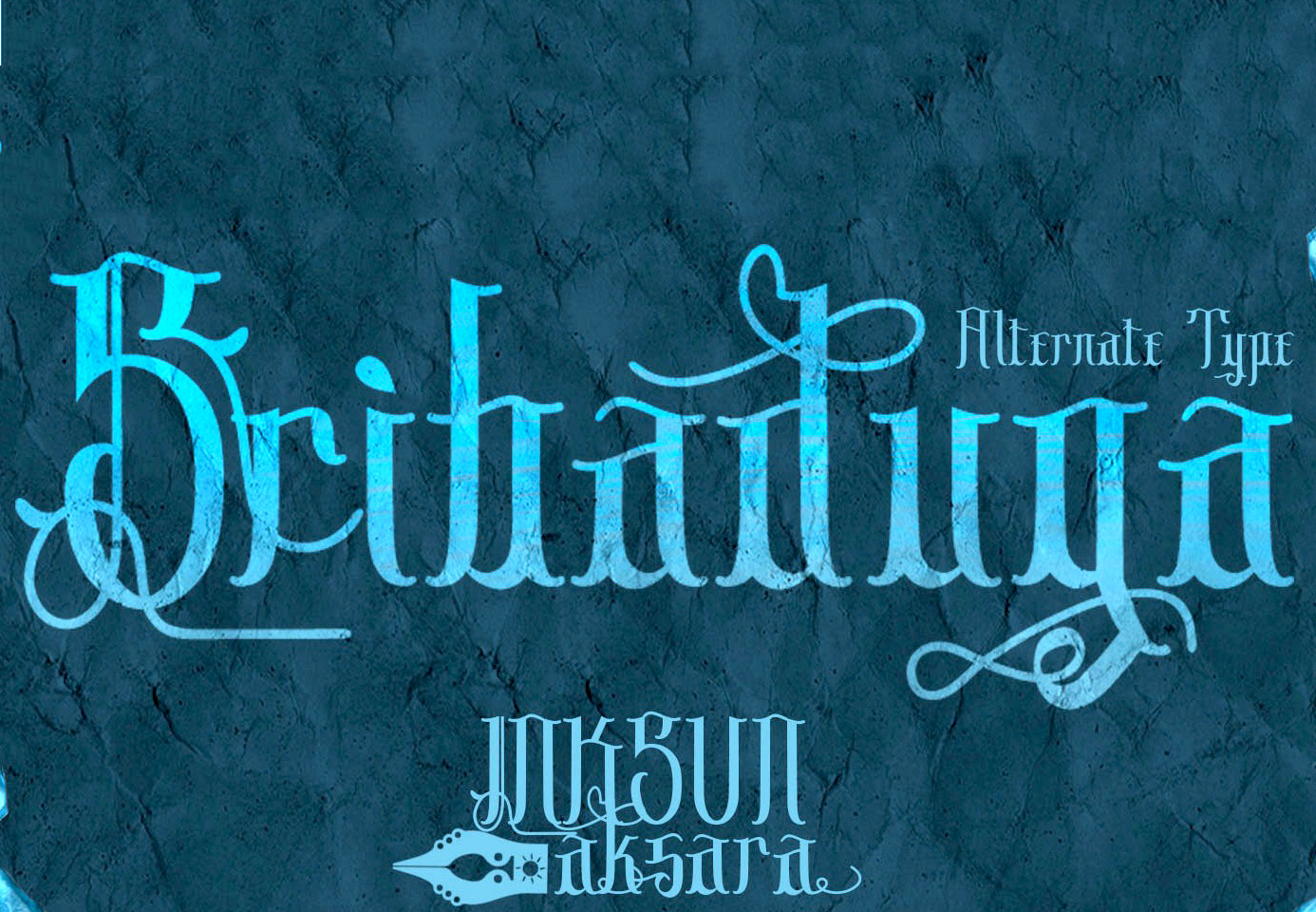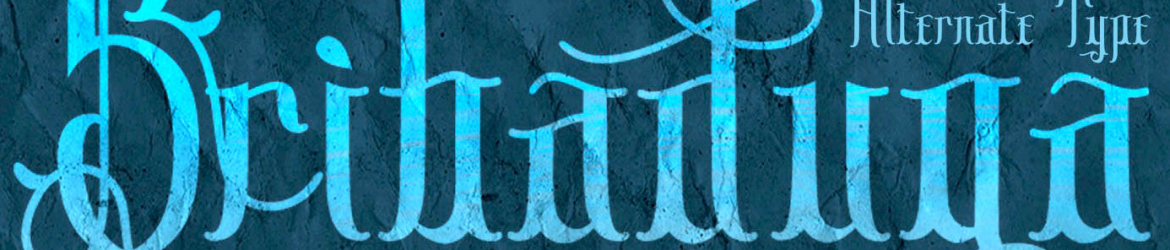
Sribaduga Font – Download Grátis
Sribaduga é uma fonte divertida inspirada nas letras gravadas nos anúncios de placares vintage dos anos 1800s. Perfeito para designers que desejam criar postais retro, capas de livros e outros trabalhos com temas vintage. Com linhas fortes e formas arredondadas, Sribaduga captura o espírito nostálgico e original desses anúncios antigos em suas placas. É uma escolha ideal para quem quer transmitir um sentido de tempo passado em seu próximo design. Esta fonte de display é perfeitamente adaptada à estética visual dos anos 1900, tornando-a uma ótima opção para aqueles que desejam criar designs memoráveis e icônicos.